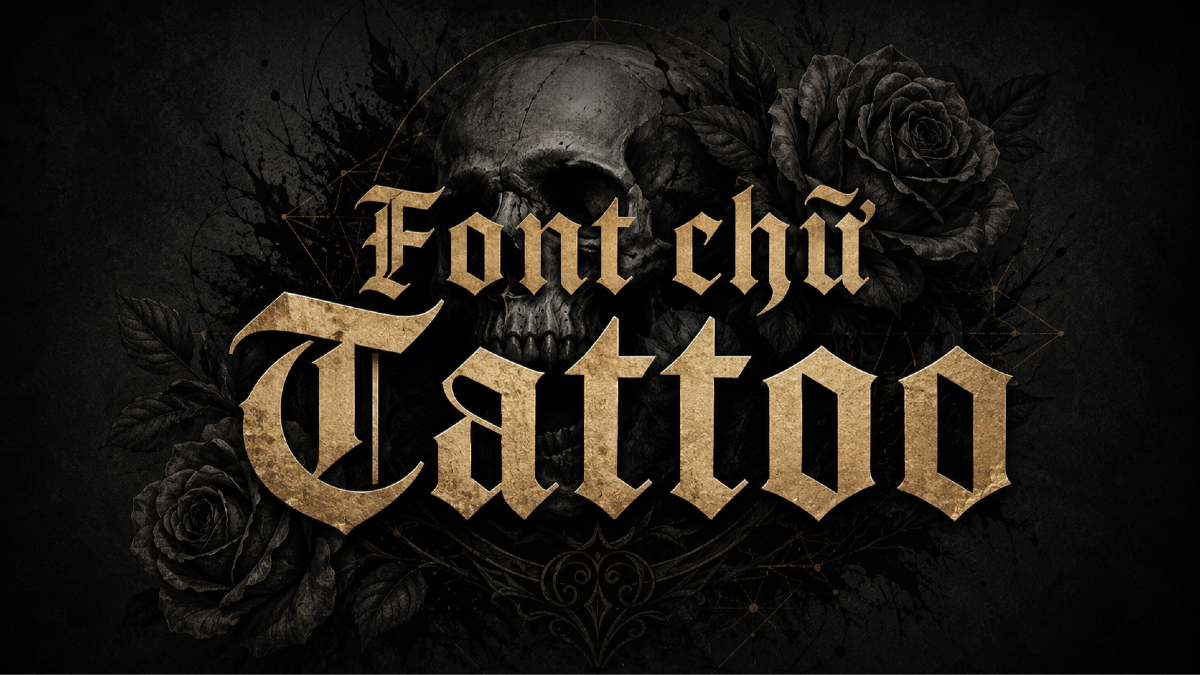
Font chữ Tattoo (phông chữ xăm nghệ thuật) là nhóm các phông chữ mang đậm phong cách đường phố, cá tính mạnh mẽ, nổi loạn và đầy tính biểu tượng, lấy cảm hứng từ các hình xăm nghệ thuật trên cơ thể. Với các đường nét uốn lượn sắc sảo của dòng Chicano, sự uy nghiêm của chữ Gothic hay nét cổ điển của số La Mã, nhóm phông chữ này là lựa chọn hoàn hảo cho các thiết kế thời trang Streetwear, bao bì phụ kiện độc lạ, nhãn bia thủ công và các ấn phẩm mang phong cách Underground. Doozypack.vn cung cấp link tải Font chữ Tattoo trọn bộ chuẩn kỹ thuật, giúp bạn sở hữu kho phông chữ xăm độc đáo, hỗ trợ tiếng Việt mượt mà để hiện thực hóa mọi ý tưởng thiết kế phá cách.
Các kiểu chữ Tattoo đẹp và phổ biến nhất hiện nay
Nghệ thuật xăm hình sở hữu rất nhiều trường hợp Typography khác nhau. Dưới đây là những kiểu chữ Tattoo đẹp và được các designer săn lùng nhiều nhất:
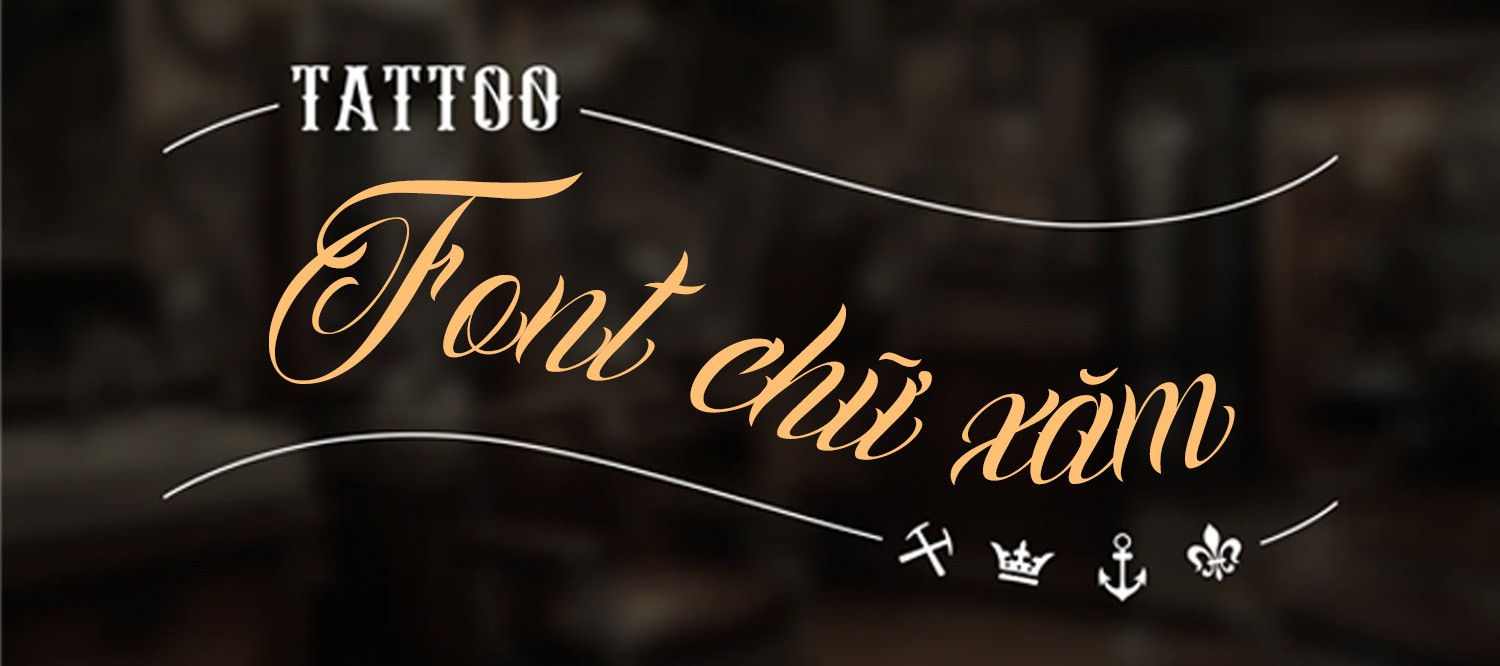
Phong cách Chicano & Script uốn lượn đường phố
Đây là dòng Font chữ xăm Tattoo kinh điển xuất phát từ văn hóa gangster Mexico-Mỹ. Đặc trưng của nhóm này là các đường nét viết tay uốn lượn cực kỳ uyển chuyển, các nét vuốt đuôi (swashes) vươn dài đầy kiêu hãnh. Khi được Việt hóa chuẩn Unicode, các bộ Font chữ Tattoo đẹp này giúp bạn dễ dàng tạo ra những dòng tiêu đề mang đậm chất tự sự và bụi bặm.
Font chữ La Mã Tattoo (Roman Numerals) cổ điển
Các con số La Mã (I, II, III, IV, V…) với các đường chân chữ (serif) sắc lẹm thường được sử dụng trong các hình xăm kỷ niệm mốc thời gian. Trong thiết kế bao bì và thời trang, việc sử dụng Font chữ La Mã Tattoo mang lại cảm giác hoài cổ, trang trọng và đầy tính kỷ luật, rất hợp để in trên các hộp quà tặng hoặc nhãn mác sản phẩm giới hạn (Limited Edition).
Font chữ xăm Gothic (Blackletter) ma mị và uy quyền
Đại diện cho trường phái Trung cổ gai góc, phông chữ Tattoo dòng Gothic sở hữu các khối chữ đặc quánh, góc cạnh và vô cùng uy quyền. Nhóm font này thường xuất hiện trên bao bì các dòng bia thủ công (Craft Beer), áo thun rock band hoặc hộp đựng phụ kiện gaming cá tính.
Ưu điểm nổi bật của bản font chữ Tattoo Việt hóa
Khi ứng dụng các phông chữ xăm nghệ thuật vào thị trường trong nước, sự chỉn chu về dấu câu là yếu tố quyết định đến tính chuyên nghiệp của bản thiết kế:
- Khắc phục triệt để lỗi dấu tiếng Việt: Phiên bản Việt hóa đã được đội ngũ thiết kế trau chuốt thủ công từng dấu câu. Các dấu sắc, huyền, hỏi, ngã, nặng được vẽ đồng điệu với cấu trúc nét chữ gốc, không gây cảm giác chắp vá hay làm biến dạng phong cách nghệ thuật.
- Hệ thống ký tự mở rộng đa dạng: Kho 1001 Font chữ Tattoo cung cấp hàng nghìn biến thể ký tự trang trí, giúp bạn thỏa sức sáng tạo các mẫu Form chữ Tattoo độc bản cho thương hiệu.
| Phong cách Font | Đặc điểm thị giác | Ứng dụng đề xuất tại Doozypack.vn |
| Chicano Script | Uốn lượn, bay bổng, bụi bặm | Logo thời trang Streetwear, tên thương hiệu trên túi giấy. |
| Gothic Blackletter | Góc cạnh, ma mị, sắc sảo | Nhãn chai Craft Beer, hộp đựng phụ kiện hầm hố. |
| Roman Numerals | Cổ điển, kỷ luật, trang trọng | In mốc thời gian thành lập công ty, hộp quà giới hạn. |
03 Ứng dụng thực tế của font chữ Tattoo trong sản xuất bao bì tại Doozypack.vn
Sự cá tính và nổi loạn của các Tattoo Font chữ mang lại hiệu ứng thị giác đắt giá trên các dòng sản phẩm bao bì thực tế do Doozypack.vn sản xuất:
- Bao bì thời trang Streetwear & Sneakers: Tiêu đề thương hiệu in bằng Font chữ đẹp Tattoo trên hộp carton sóng hoặc túi giấy Ivory cán màng mờ tạo cảm giác cá tính, sành điệu và cực kỳ thời thượng.
- Nhãn dán chai Bia thủ công & Rượu mạnh: Nét chữ Chicano hoặc Gothic in màu trắng hoặc ép kim bạc trên nền nhãn đen tạo nên vẻ ngoài đậm chất Underground, thu hút giới trẻ.
- Hộp đựng phụ kiện xăm hình & Đồ chơi nghệ thuật: Dùng cho tên dòng sản phẩm hoặc các slogan ngắn, tạo nên sự đồng bộ tuyệt đối về mặt phong cách thị giác.
Lưu ý kỹ thuật khi in ấn với phông chữ nghệ thuật Tattoo
Việc sản xuất bao bì thực tế sử dụng các phông chữ có đường nét phức tạp đòi hỏi sự am hiểu kỹ thuật chuyên sâu tại xưởng in Doozypack.vn:
- Kiểm soát hiện tượng tràn mực (Dot Gain): Các khoảng hở bên trong chữ cái của font Gothic hoặc Script khá hẹp. Khi in trên giấy có độ thấm mực cao như giấy Kraft, mực có thể bị lan làm bít các lỗ hở. Bạn nên giữ size chữ tiêu đề tối thiểu từ 10pt trở lên.
- Lựa chọn hệ màu tương phản mạnh: Phông chữ xăm nghệ thuật đẹp nhất khi phối cùng các tông màu tối giản như Đen – Trắng hoặc tạo điểm nhấn bằng kỹ thuật ép kim bạc.